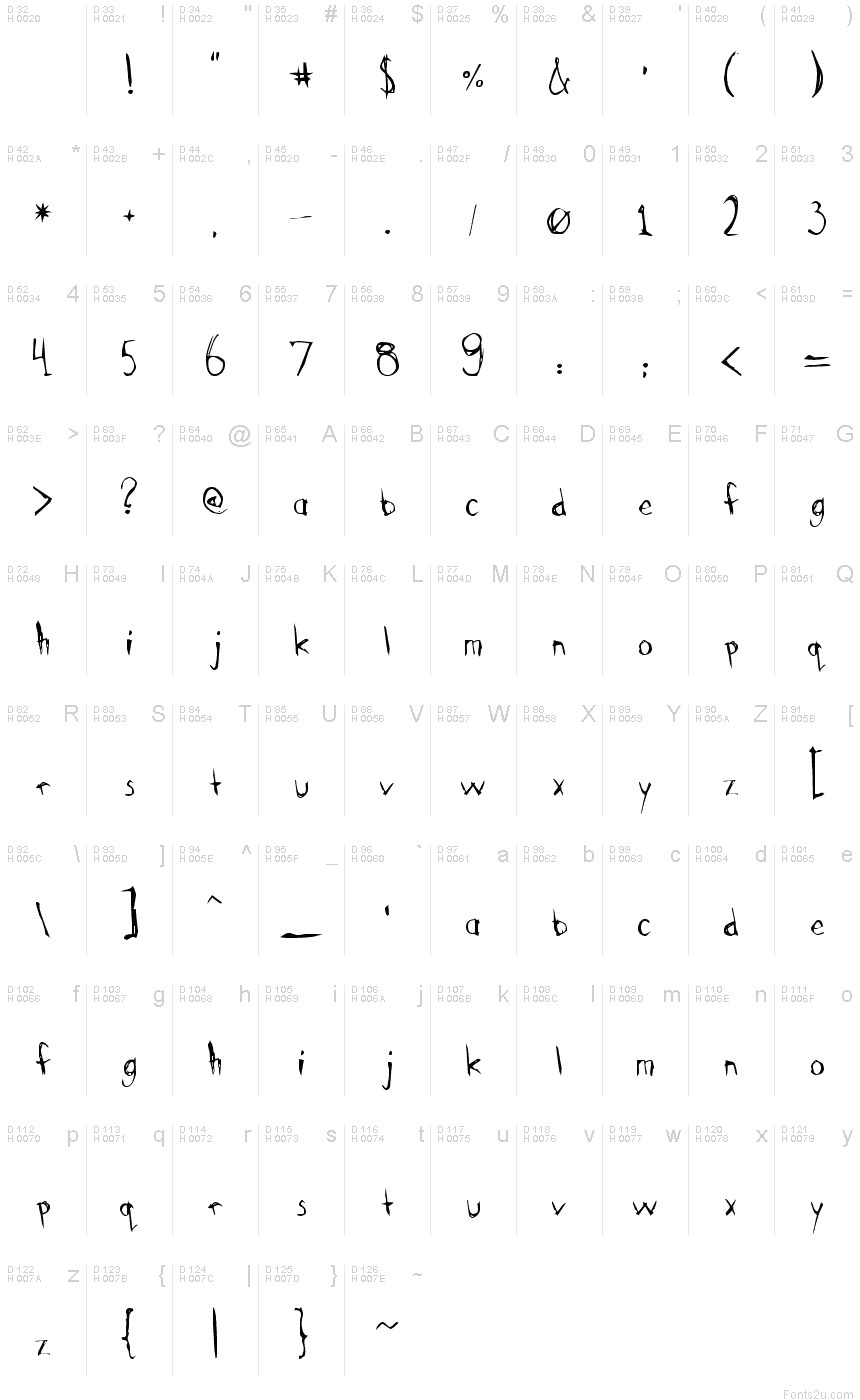
BootyScratch
Booty Scratch هو خط مجاني مكتوب باليد يبدو وكأنه خُطّ مباشرة على الورق. الحروف طويلة وحادة وتتراقص بطاقة عصبية، كأنها رُسمت بحركة حبر واحدة متوترة. الخطوط الرفيعة والمخربشة تمنح كل كلمة لمسة خام لا يمكن التنبؤ بها، مما يجعلها تبدو صاخبة وحيوية.
مع Booty Scratch، يمكنك دفع عناوين أفلام الرعب، وملصقات الحفلات، ومجلات البانك، وأغلفة الألبومات، ودعوات الهالوين، وصور يوتيوب المصغرة نحو حالة من الفوضى الكاملة. يعمل هذا الخط المجاني بشكل أفضل عند استخدامه بأحجام كبيرة حيث تبرز قوامه المسنن وتتضح تفاصيله؛ نسّقه مع خط أساسي بلا زوائد (Sans Serif) نظيف ومحايد للنص الأساسي للحفاظ على القراءة السلسة مع الحفاظ على ذلك الطابع الخطير.
bootyscratch by taber. 1998.